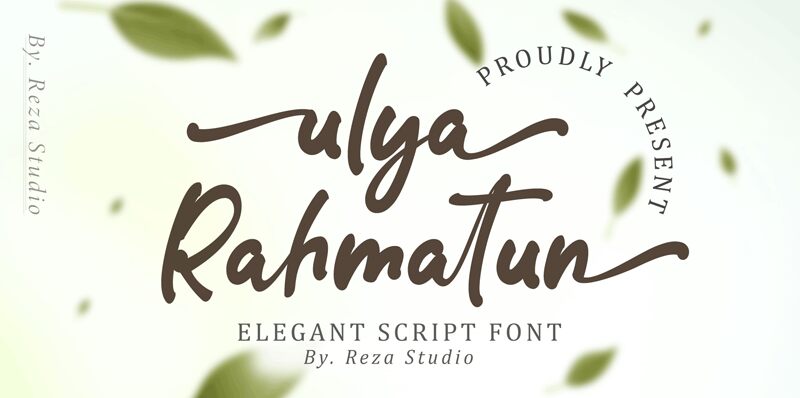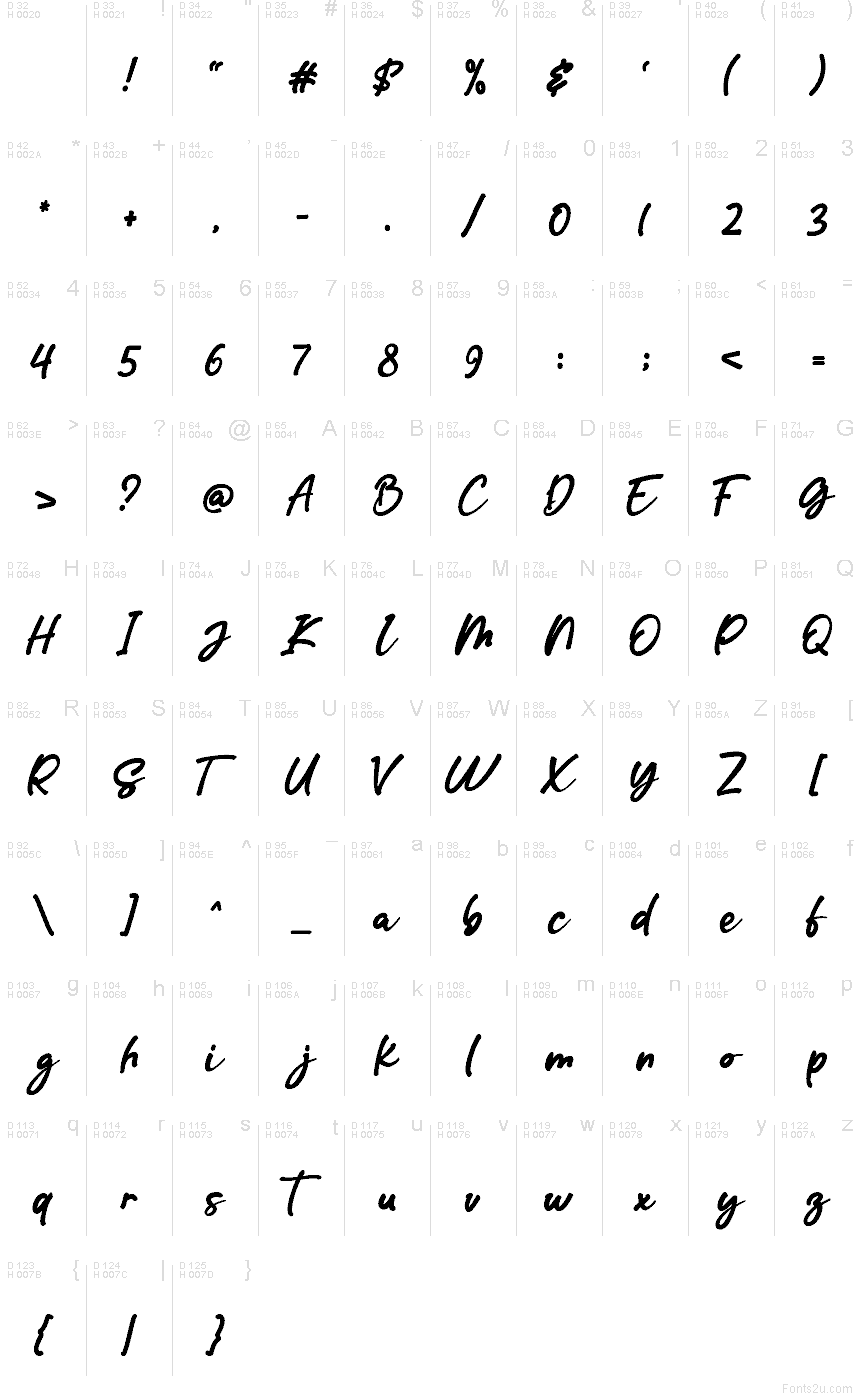
Ulya Rahmatun ist ein kostenloses Pinsel-Script mit breiten, fließenden Strichen und der Leichtigkeit schneller Handlettering-Schriften. Abgerundete Verbindungen, wechselnde Strichstärken und weit geschwungene Linien verleihen den Buchstaben einen lebendigen Signatur-Stil mit genau der richtigen Unregelmäßigkeit, um eine persönliche Note zu wahren.
Die entspannte Dynamik eignet sich gut für Beauty-Branding und Hochzeitseinladungen, kann aber auch Kaffeeverpackungen und Musikplakaten eine freundliche, handgemachte Note verleihen. Die großzügigen Schleifen und weichen Formen harmonieren natürlich mit romantischen, kreativen und handwerklichen Themen. Bei der Produktidentität kann das Script eher als einprägsames, handgezeichnetes Logo statt als gewöhnlicher Begleittext dienen.
Zu den Features gehören Anfangs- und End-Schwünge sowie Ligaturen.